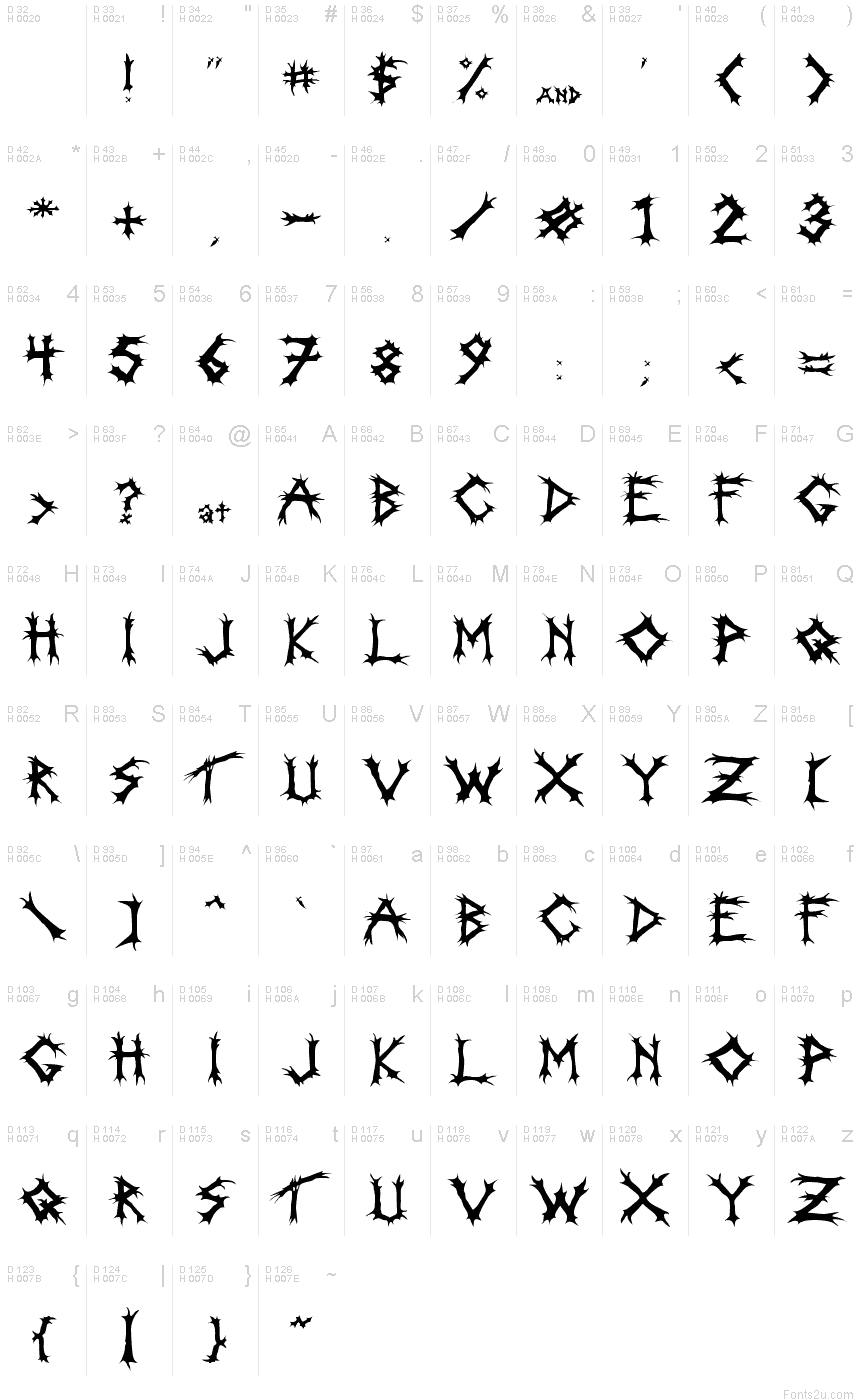
Incantation è un font display gratuito e distorto, che sembra nato da spine nere e radici aggrovigliate. Ogni lettera si frammenta in punte acuminate e bordi frastagliati, conferendo alle tue parole un'energia cruda e occulta, come se fossero incise nella pietra o bruciate nel legno. La spaziatura rimane sorprendentemente leggibile, così ottieni un'estetica aggressiva e rituale senza perdere leggibilità nei titoli.
Con Incantation, puoi spingere locandine horror, loghi di band metal, flyer per Halloween, copertine di romanzi dark fantasy, titoli di giochi o miniature YouTube in territori da incubo. Questo font gratuito dà il meglio di sé in grande e in grassetto, lasciando respirare spine e uncini; abbinalo a un carattere sans serif semplice e pulito per il testo principale, in modo che questa tipografia selvaggia rimanga al centro della scena.